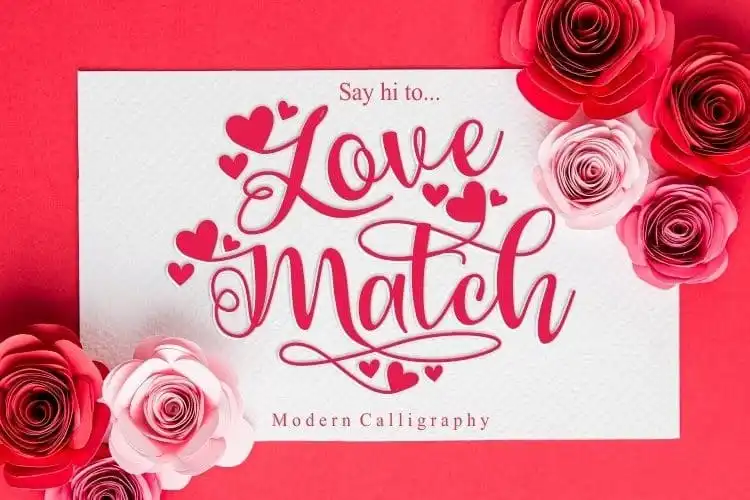
Love Match Calligraphy Font – Fonte Grátis
Love Match Calligraphy Font
A Love Match Calligraphy Font é a escolha perfeita para quem procura uma fonte de escrita script romântica e envolvente. Esta elegante fonte é ideal para criar um estilo único em diferentes tipos de projetos, desde logomarcas e identidades visuais até embalagens, publicações e posts nas redes sociais. Com seu design delicado e versátil, a Love Match está à disposição para personalizar seus trabalhos mais personais, como cartões de aniversário, cartelas de estação ou designs de casamento. A fonte é uma ótima opção para atender aos requisitos do marketing digital, criando texturas atraentes para posts e materiais publicitários. Além disso, sua personalização perfeita pode ser usada em fotografias, como um toque único nos créditos de crédito ou até mesmo em eventos especiais onde uma escrita elegante torna qualquer momento mais memorável. Com seu design romântico e sofisticado, a Love Match é definitivamente o atalho para criatividade no que diz respeito às letras do seu estilo.